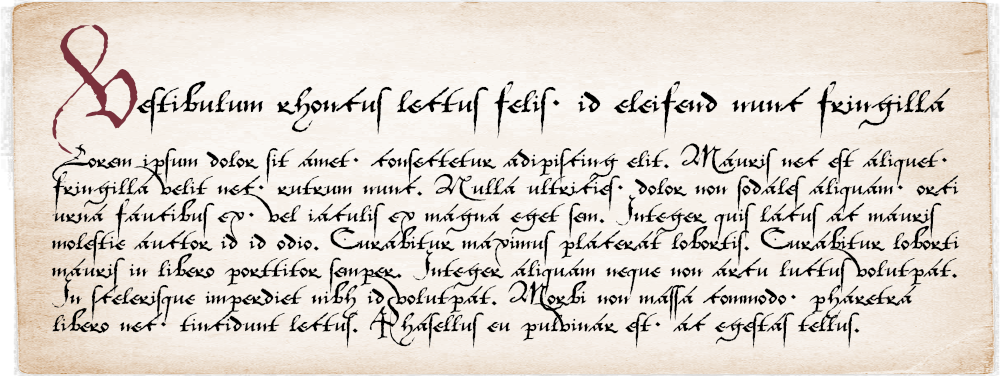
Suche eine alternative Schrift zur Escritura Cortesana
ich bin auf der Suche nach einer alternativen Schriftart die ähnlich ist wie die "Escritura Cortesana" Schreibschrift. (bei Wikipedia zu finden) eventuell hätte ja sogar jemand die Möglichkeit mir genau diese Schrift nachzustellen?
Ich benötige diese für ein kleines Tattoo Vorhaben mit spanischem Text.
Vielleicht passt die Spanish Court Hand von der Walden Font Co.? Oliver Weiß ist auch Mitglied in diesem Forum.
Abend, vielen Dank für die schnelle Meldung. Die Schrift geht schon genau in die Richtung, allerdings fehlt mir da irgendwie noch etwas.
Damit nicht jeder googlen muss, wie die eigentlich aussieht:
Die hat ganz andere Buchstabenformen – kommt es dir darauf an oder allgemein auf eine so verschnörkelte Schreibschrift?
Ich würde sagen es kommt auf beides an. Ich finde die Schrift im Allgemeinen super und habe dazu einfach keine alternative gefunden die mir persönlich so zu sagt. Ich befürchte, dass es darauf hinaus laufen wird das ich jemanden suchen muss der mir den Schriftstil kopieren kann per Hand. Und eine PC-Schrift dort niemals drankommen wird.
Ich würde da einen Tattoo-Artisten suchen, der selbst ein Händchen für Handschriften hat und dann gucken, was dem so einfällt. Tattoos sind ja was anderes als mit Feder auf Pergament/Papier geschriebenes. Ist wie mit Logo-Design, auch da würde ich eher nach einem Künstler schauen, als irgendwas generisches aus dem PC zu nehmen.
Und wenn ein/e Tattoo-Artist/in ein Händchen für so etwas hat, dann reicht u.U. schon ein Ausdruck des Bildes aus dem Wikipediaartikel als Vorlage aus.